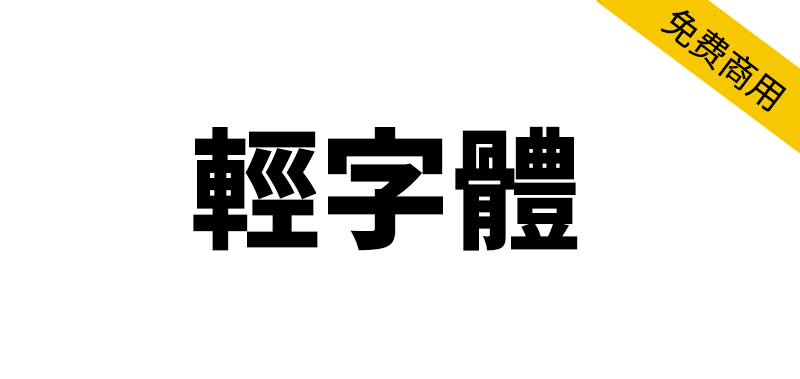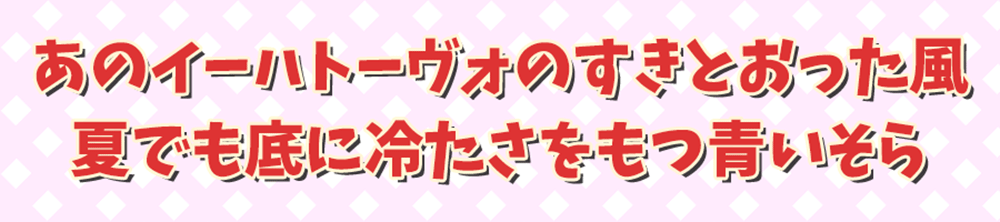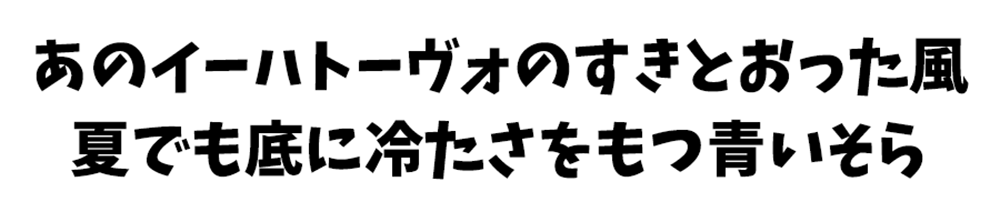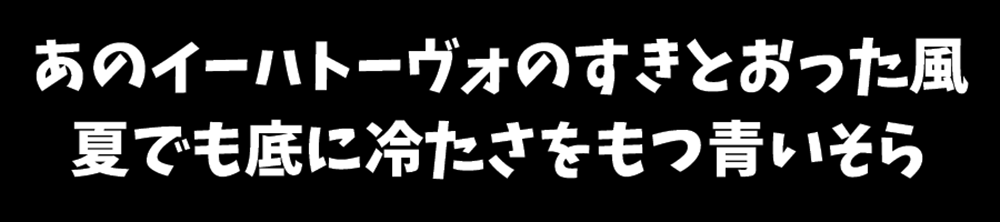
轻字体(けいふぉんと)是一款轻盈而富有节奏感的字体,虽属于黑体(Gothic)设计范畴,但其平假名与片假名的造型尤为灵动流畅。字体兼具手写骨架特征,亦可归类为POP体。多数POP体字怀(フトコロ)偏大,而本款字体通过收窄字怀,呈现出更为利落的视觉效果。
在假名设计中融入了与品牌或作品形象相契合的「率真」「质朴」「明快」「跃动」等特质。字体曲线相对舒缓,假名由不过分夸张的曲线与直线构成。其笔画挑钩处颇具特色——如「に」的第二笔、「た」的第三笔等通常被黑体省略的「跳钩」,在此却保留了充满活力的上扬笔触,宛若跳跃的韵律。
适用于标题设计的特性,采用比例字体(Proportional Font),假名与西文字符间距会根据字形自动优化,确保横排/竖排时均能实现均匀排版,较粗的笔画使其更适配标题与标语使用。若用于正文,建议仅局部强调少量字符,以避免版面压迫感。
軽快でリズミカルなフォントです、ゴシック体のカテゴリーに入るデザインですが、ひらがな・カタカナは非常に軽快でリズミカルな形です。 手書きの骨格も持ち合わせていて、ポップ体とも言えるデザインのフォントです。 ポップ体は大きめのフトコロのフォントが多いですが、本フォントはフトコロが小さめで、スマートな印象を与えます。
ロゴタイプや作品のイメージに近い「素直さ」や「実直さ」、「明るい感じ」「弾ける感じ」をひらがな・カタカナの各要素に散りばめています。フォントのカーブは比較的に緩やかで、それほど激しくない曲線と直線で仮名文字が成り立っています。 はねる箇所についても特徴的な一面を持っています。「に」の2画目、「た」の3画目などは多くのゴシック体で省略される「はね」ですが、 ジャンプするかのように元気なはねが付いています。
見出しに適したフォントです、プロポーショナルフォントで、ひらがな・カタカナ・英数字の字間はそれぞれの文字幅によって調整してあります。 そのため、組んだ時に等間隔で文字が並ぶことが期待できます(これは横書きだけでなく縦書きにも言えることです)。フォント自体は太めなので、本文よりは見出し・タイトルなどに向いています。 本文で使用する場合は、強調する数文字程度にこのフォントを指定するくらいなら、デザイン上もおそらく問題なく使用できます。